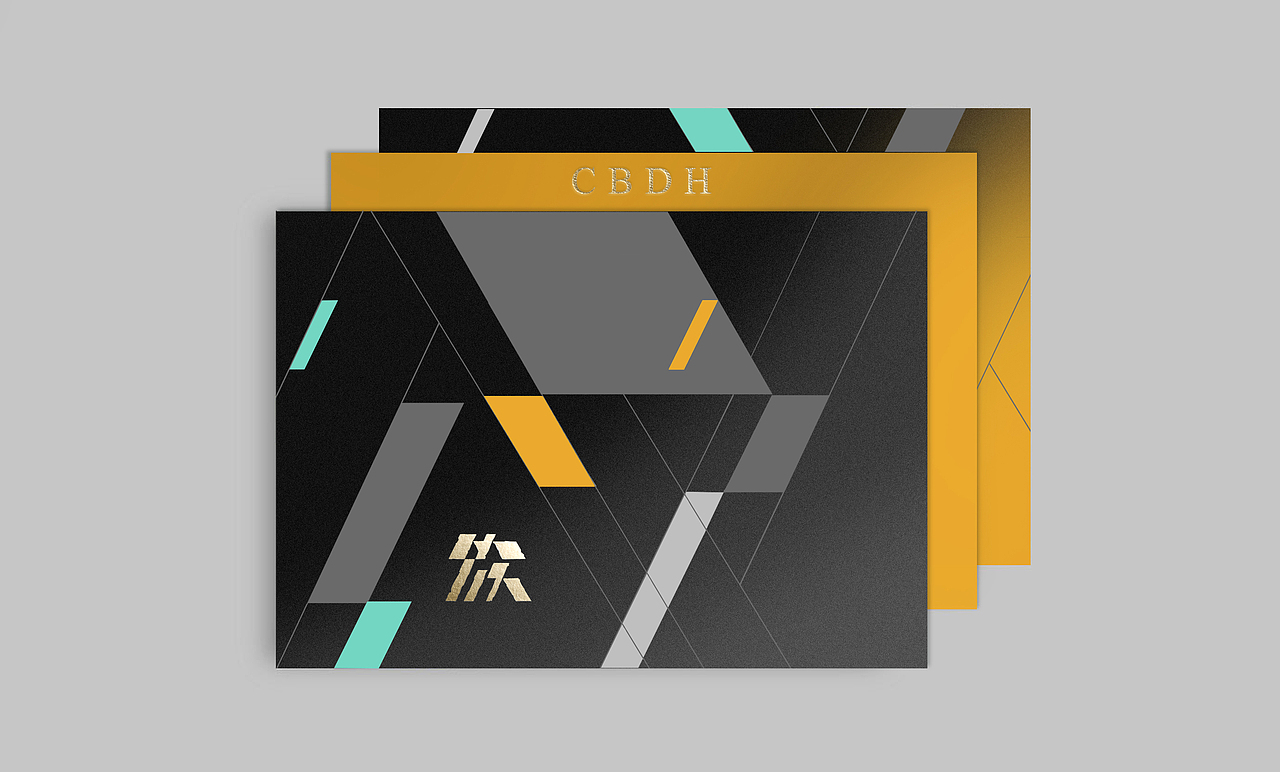
西影集团:
简称“西影”,1958年8月成立。前身为西安电影制片厂,是中国六大电影集团之一,是国家电影产业布局的四大集团之一。
在全国电影制片单位中,西影第一个在国际A级电影节获得最高奖项,获国际奖项数量位居全国第一,影片出口量全国第一。总共获得国内外奖项300多项,出口影片80多部。
西影是第五代电影导演的发祥地,代表影片《霸王别姬》《老井》《红高粱》《图雅的婚事》《我的一九一九》《大话西游》系列等等。
标志塑造了西部升起的太阳下奔跑的人,太阳象征电影艺术如同太阳的光芒,照亮整个世界与人类的文明;太阳从西边升起,象征西部电影的辉煌与光明未来。奔跑的人隐喻了西影人追逐艺术理想的不朽精神。
荷花园-晋南印象:
传承理念与继承晋南文脉,用设计语言向消费者表达晋南文脉渊源与荷花园的现代发展前景。
图形立意明确,细节细腻生动。感受晋南文化的独特魅力与民俗的历史底蕴。
图形采用了木版画的肌理去表现,让探访的人们领略鲜活的生活气息。
国芳百货:
国芳百货是一家以大型连锁零售业为龙头多项产业并行的企业,在全国享有极高的声誉。是具有相当影响力的时尚先锋品牌。
标志源于九色鹿的故事,加入了国粹艺术的渲染,九色鹿文化识别与丝路文化融合,加上佛教背光凝练升华圣洁之光,深化了品牌的内涵,其独有的中国韵味,也让人品味无穷。
标志以篆体的 “芳” 字为元素进行设计,将九色鹿的典雅姿态融入其中,浑然天成的优雅,俏丽与时尚俱在。
丝路欢乐世界:
丝路欢乐世界,作为“丝绸之路风情城”项目下属主题公园板块,在标志的设计上,要求原创作品既能体现项目独立性以及自身特色,又能体现项目作为单独板块与主体项目之间的紧密关联。
图形是一匹由气球图形组成的骆驼。骆驼是丝路主题乐园的专属图形,气球是乐园的元素提炼,让观者体味轻松愉快与自由心情;色彩与图形代表了丝路主题乐园的六大板块;是与时代话题结合的旅行主题乐园的专属图形。
图形巧妙的连接与错落,同时体现出了一带一路的线路,是有着时代精神的美好设计。
古田路 Brand创意呈现Ⅳ:
古田路《Brand创意呈现Ⅳ》选用了薛定谔的猫作为设计创意点,个性理念独具的封面及系列推广画面。体现了古田路品牌带来前瞻性的设计思考与洞察。
“薛定谔的猫” 是著名的量子力学实验,从宏观尺度阐述微观尺度的量子叠加原理的问题。
创意用这只“奇异的猫”说明了世界的不确定性。而不确定性代表了创意与艺术的自由思想。
西安文化科技创业城:
细胞的分子裂变、成长速度,是自然界中最快速的。图形寓意了文化科技创业城发展与培养的速度,不墨守成规,成长性好、具有新型发展态势。随时汲取新的能量。
创意又源自链条,诠释全产业链的完善与联动。活力传送,构建出创新生态链,是有着专属定义的视觉符号系统。
标志同时也是XCIC的字母缩写,具有独特而清晰的识别力。适合在未来的营销推广过程中灵活使用。
屋极酒店:
屋极酒店(WUJI Hotel)的logo的设计具有北欧设计的干净利落与简洁,充满韵律、质感非凡。
WJ的字母变形,是酒店建筑的外观描绘,图形超越了外在、把握了简即是繁的精髓,是旅客心中的真我乌托邦。
logo图形又含有包豪斯的现代结构,于现代设计思路中解读酒店的至高含义:穹顶之下,人心之上。
清盈:
荷花是有着中国文化代表的图形,是神圣净洁的象征。出尘离染,清洁无瑕。
船有着接引、度过的含义,启程与抵达。不仅仅是“发思古之幽情”,更重要的是延续哲思与文化。
读书的形象寓意了文人的精神生活,增长智慧的同时涵养静气,妙处无穷。
创意取自《莲舟仙渡》图,一名风雅之士乘坐在莲花瓣上,悠然的读着书,顺水而行。超越现实的存在,描绘出了现实中寻找不到的完美的人性,寓意了精神的超脱与理想诗意的生活。既能表现出对现实的超越,又有着追文溯源的脉络,具有深邃独特的专属感。
簇 - 精品酒店联盟:
创意源自汉字的“簇”,由建筑美学延伸到字体结构,衍生出复合涵义,方寸间领略深刻含义。
既有中国民居的历史底蕴,又含有包豪斯的现代结构,于两种设计思路的融合中解读汉字。
群落概念,和而不分、和谐统一。
“以酒店为旅行目的”,是精品设计酒店联盟独特个性的表现和浪漫主义的独特体现。
不断探索、超越外在、把握精髓,设计师心中的真我境界。
长江生态保护基金会:
长江被称作中国生物多样性基因库,江豚这样的高等水生哺乳动物的生存状况,
是水系生态的直观而重要的指标。
《赏未之贰拾肆节气历》之大雪:
贺冰凇原创插画-《大雪》,创意将节气与古典文化进行了结合。
《大雪》描绘了在大雪的节气中,天地清寒,目之所及寒色纷纷笼罩四野;古村寒江几乎没有人的踪迹,孤独的渔翁一人一扁舟于江上的意境。山川流云静止般的美好,天地间苍茫无极,向晚苍苍南北望,鸥鹭纷飞难辨。
将民俗节气作品设计上升到艺术层面,结合古人的智慧与现代人的思索,表现丰富的生态思想,以全新的方式呈现出的是自古以来人类与自然间发生的微妙的情绪。